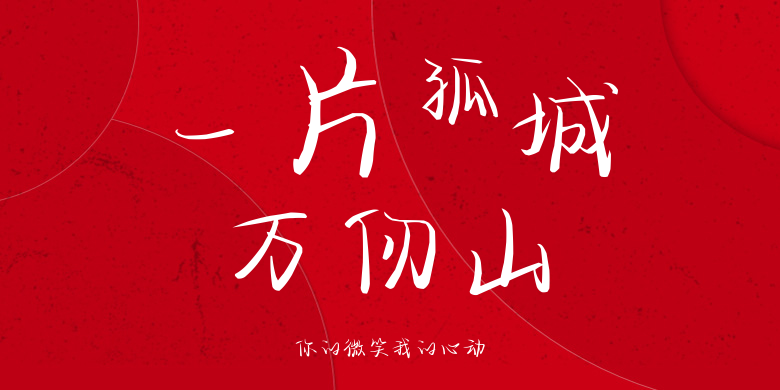
你的微笑我的心动
你的微笑我的心动,这款字体结构工整、笔画清晰,兼顾美观与易读性,适用于标题、正文、海报、包装、LOGO 等多种场景。字形优雅稳定,风格百搭耐看,适配日常排版与创意设计,让文字呈现更舒适、更具质感。你的微笑我的心动一笔一画,皆是细节,以均衡的比例、流畅的线条打造舒适视觉体验,字形端正大气,风格简约现代。无论是商业设计、品牌宣传还是日常排版,都能轻松驾驭,让文字更有格调与力量。你的微笑我的心动字体下载。